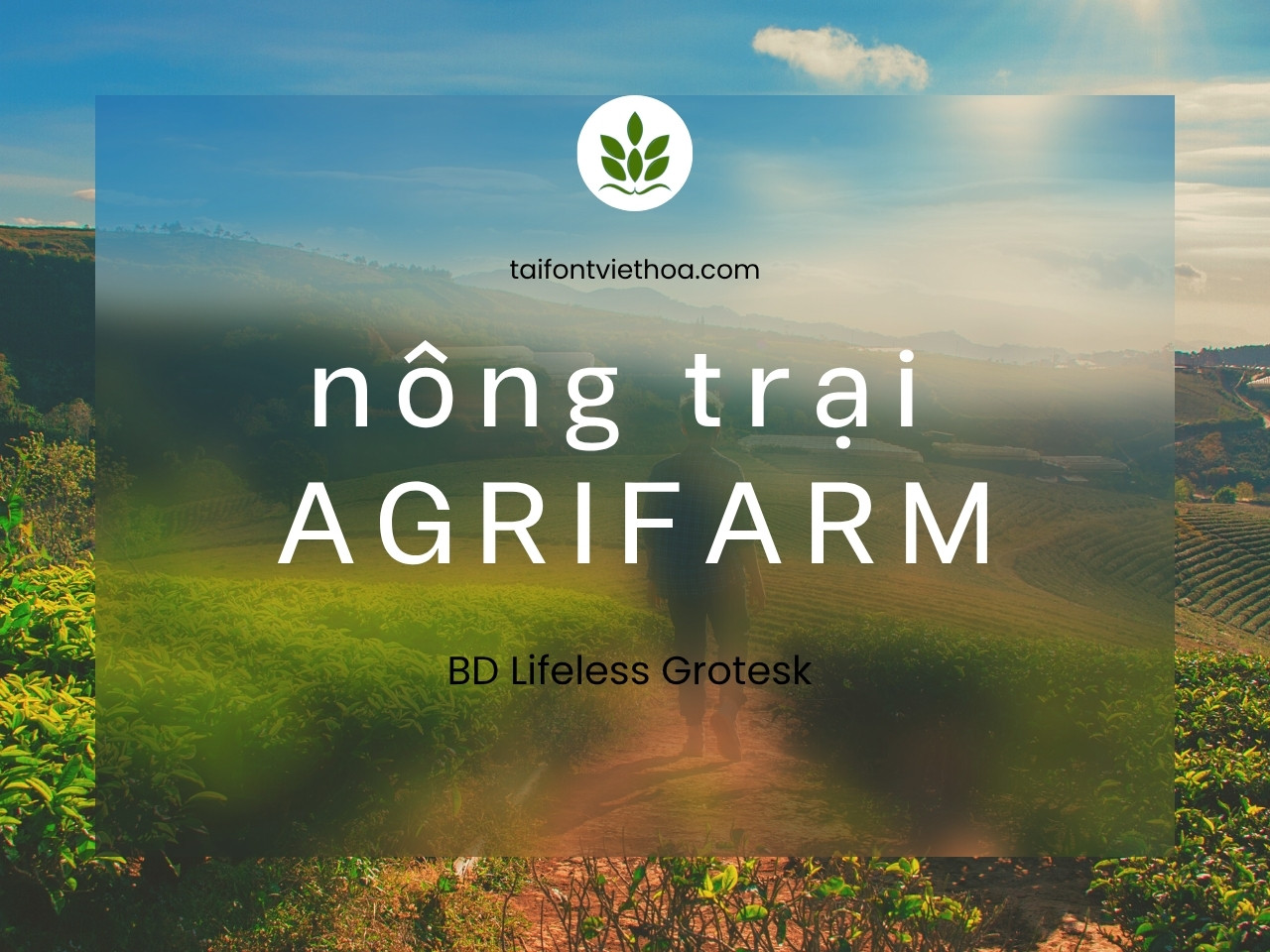
Font việt hóa Bd Lifeless Grotesk Font Tiếng Việt
Tác giả Font: Harry Dinh
Giới thiệu về font Bd Lifeless Grotesk và phiên bản Việt hóa
Bd Lifeless Grotesk là một font sans-serif độc đáo do nhà thiết kế Harry Dinh phát triển, lấy cảm hứng từ trường phái grotesk cổ điển nhưng được biến tấu lại theo hướng tối giản và hiện đại. Font được phát hành lần đầu vào năm 2023 và nhanh chóng tạo ấn tượng mạnh mẽ trong cộng đồng thiết kế nhờ cấu trúc gãy gọn, mạnh mẽ nhưng vẫn giữ được nét trung tính dễ ứng dụng. Với khả năng hỗ trợ hơn 80 ngôn ngữ toàn cầu bao gồm bảng Latin mở rộng và tiếng Việt, đây là một font chuyên nghiệp đáng chú ý.
Phiên bản Việt hóa được thực hiện bởi chính tác giả Harry Dinh, đảm bảo tối đa tính nguyên bản trong từng đường nét. Tất cả ký tự tiếng Việt, bao gồm dấu thanh và phụ âm, đều được vẽ lại kỹ lưỡng, đảm bảo tính thẩm mỹ và đồng bộ trong hệ thống font. Bd Lifeless Grotesk đã được taifontviethoa.com sưu tầm và cập nhật lại trong bộ sưu tập font cao cấp dành cho các nhà thiết kế chuyên nghiệp tại Việt Nam. Bộ font mang lại giải pháp hoàn chỉnh cho các dự án branding, giao diện kỹ thuật số và thiết kế in ấn.
Đặc điểm thiết kế và ứng dụng thực tế
Bd Lifeless Grotesk có cấu trúc đối xứng và tuyến tính, nổi bật với các đường cong tinh tế kết hợp cùng hệ thống chữ viết mạnh mẽ, không thừa chi tiết. Font có hệ thống weight đa dạng từ Light đến Bold, cho phép sử dụng linh hoạt trong tiêu đề, đoạn văn bản hoặc bảng hiển thị. Không gian giữa các chữ được thiết kế khoa học giúp tăng độ dễ đọc, đặc biệt trên các thiết bị kỹ thuật số.
Font này phù hợp với nhiều ứng dụng như thiết kế thương hiệu công nghệ, bảng chỉ dẫn, giao diện người dùng (UI), tạp chí kỹ thuật số, bao bì sản phẩm hoặc poster quảng cáo hiện đại. Các ngành nghề như truyền thông, startup, công nghệ số, giáo dục kỹ thuật hoặc bất động sản cao cấp đều có thể tận dụng Bd Lifeless Grotesk để nâng tầm hình ảnh chuyên nghiệp và hiện đại.